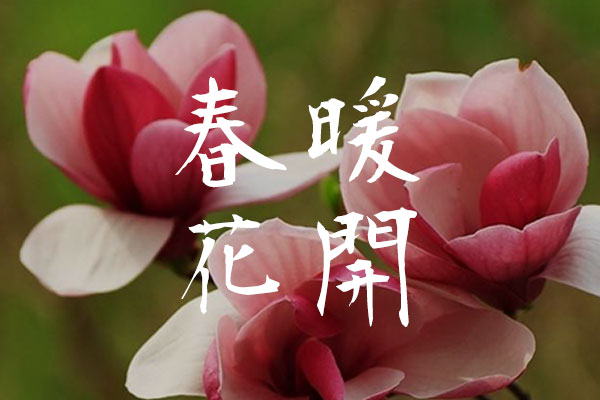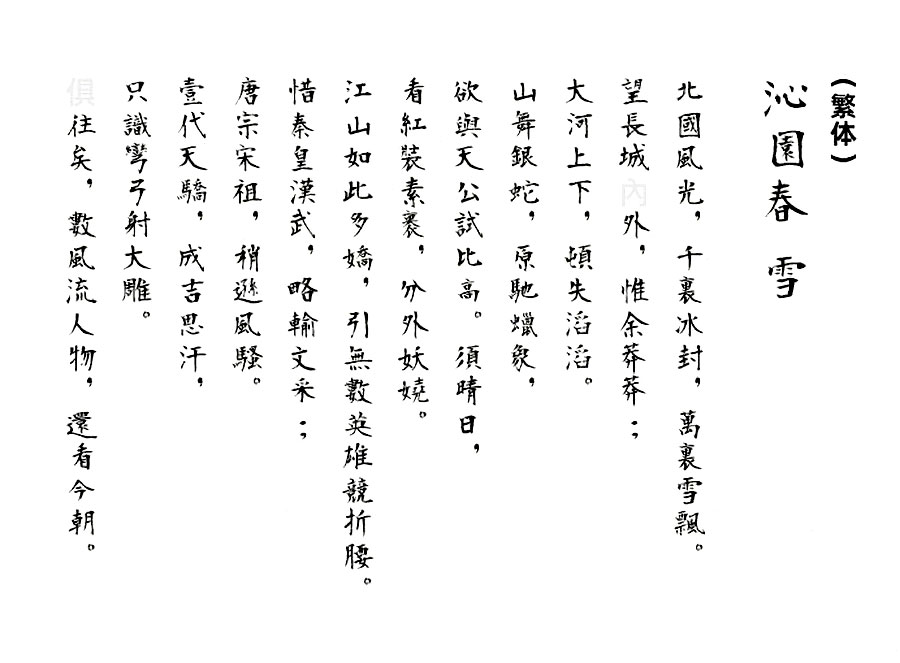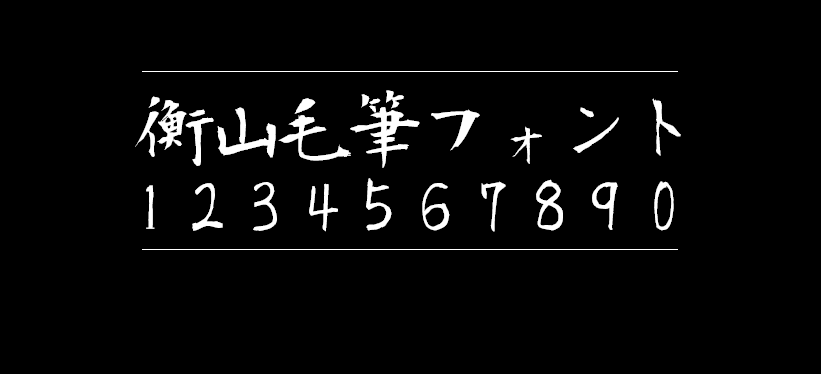
衡山毛笔体
衡山毛笔体(日文名:衡山毛筆フォント 英文名:KouzanBrushFont)是日本书法家青柳衡山老师挥毫书写的字体。 收录的字数约为13,000字。 由于字体采用的日本的JIS标准,所以支持的简体字数不多,但是繁体却是比较齐全的,所以大家也可以用这款字体来做繁体的设计。这款字体完全可以免费使用于任何用途,包括商用。